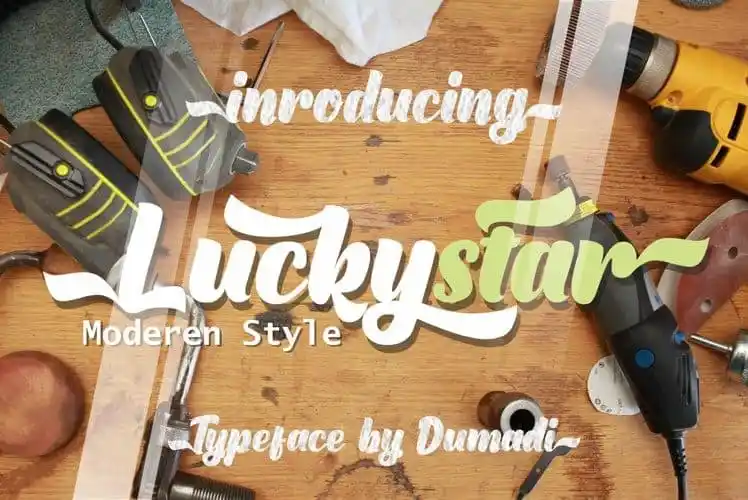
Luckystar Bold Script Font – Fonte Grátis
Luckystar Bold Script Font
A Luckystar Bold Script Font é uma nova adição à incrível categoria de tipos de letra script. Desenvolvida pelo designer DUMADI na plataforma 99designs, essa fonte atinge o ponto perfeito entre clássico e atual. Ela traz um toque nostálgico ao seu design, transportando você para os anos 60, lembrando-nos dos tempos de nossas avós e tios que frequentavam discotecas com cores vibrantes e letras em destaque. Feita para designers que buscam uma fonte forte e versátil, a Luckystar é perfeita para projetos de design gráfico e até mesmo para mockups. Seja você um designer experiente ou iniciante, esta fonte facilitará o seu trabalho, oferecendo-lhe vários recursos e opções estilísticas. Com a Luckystar Bold Script Font, você não terá que desesperadamente procurar por letras perfeitas – todas as suas necessidades de design já estão incluídas no pacote.